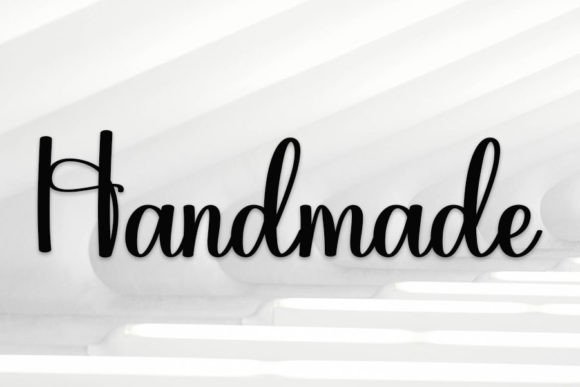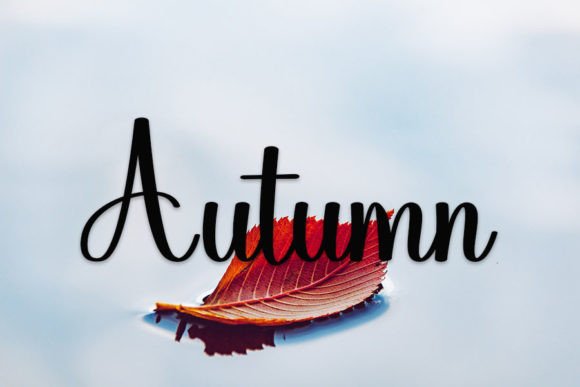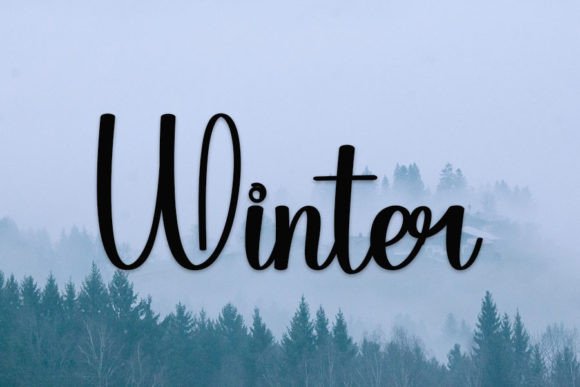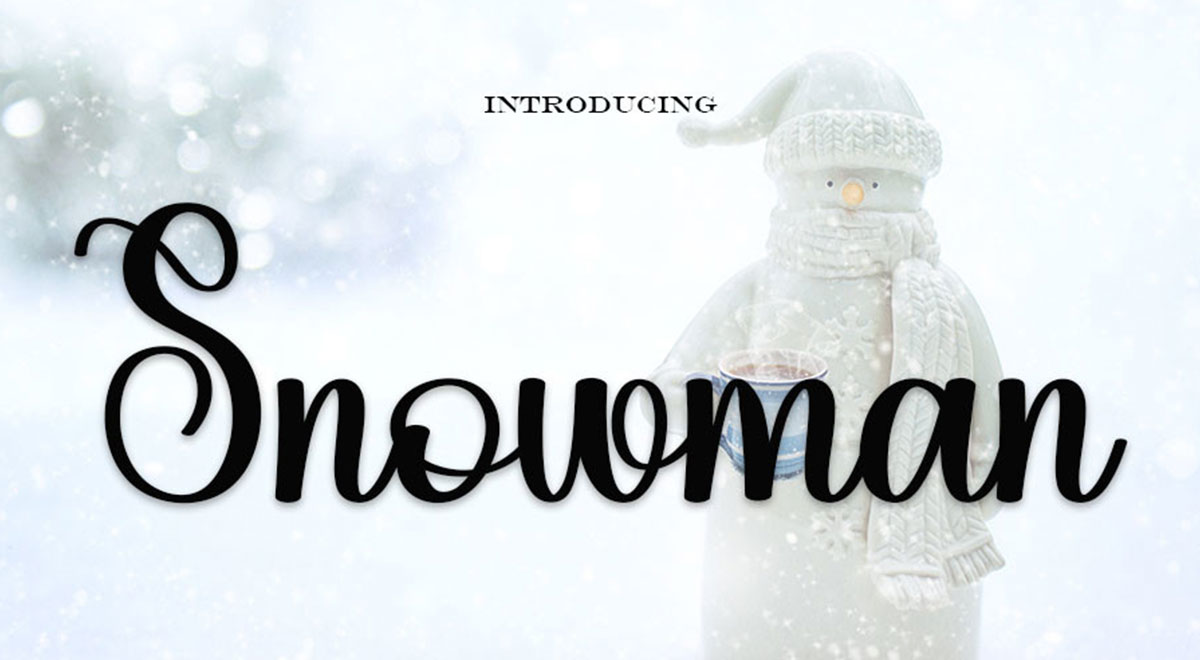
فونت Snowman انگلیسی
| ⭐ توضیحات | Snowmanis یک فونت دست نویس مرتب و زیبا است که با یک لمس ظریف توصیف شده است، مناسب برای پروژه های مورد علاقه شما عاشق سبک فوق العاده متمایز و جاودانه آن شوید و از آن برای ایجاد طرح های دیدنی استفاده کنید! |